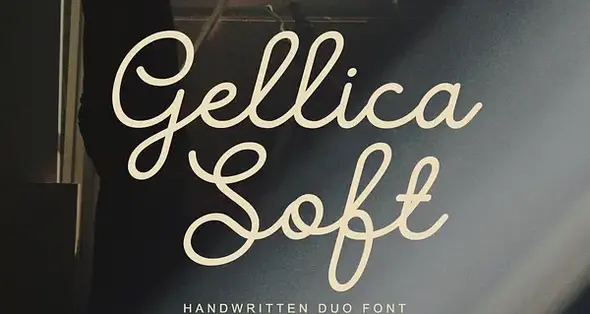
• Gellica Soft - Handwritten Font Duo
Gellica Soft یک مجموعه فونت دست‌نویس است که از دو نسخه تشکیل شده: نسخه Italic آن یک فونت دست‌نویس مونو‌لاین است و نسخه Regular آن ترکیبی از یک مدل سنس سریف مونو‌لاین با کاراکترهای اسکریپت است. هدف از طراحی این فونت، الهام گرفتن از طرح‌های ساده اما مؤثر این دوران بوده است. این فونت‌ها برای لوگوی محصول، لوگوی کارت عروسی، لوگوی برند لباس، طراحی‌های وینتج و بسیاری موارد دیگر عالی هستند.
Gellica Soft is handwritten font duo, with the concept of italic version is a monoline handwritten font, and the regular version is equipped with a sans serif monoline model combined with a script character. The goal was to take the simple but effective designs from this era. This fonts are great for product logo,wedding card logo, clothing brand logo, Vintage design and much more.